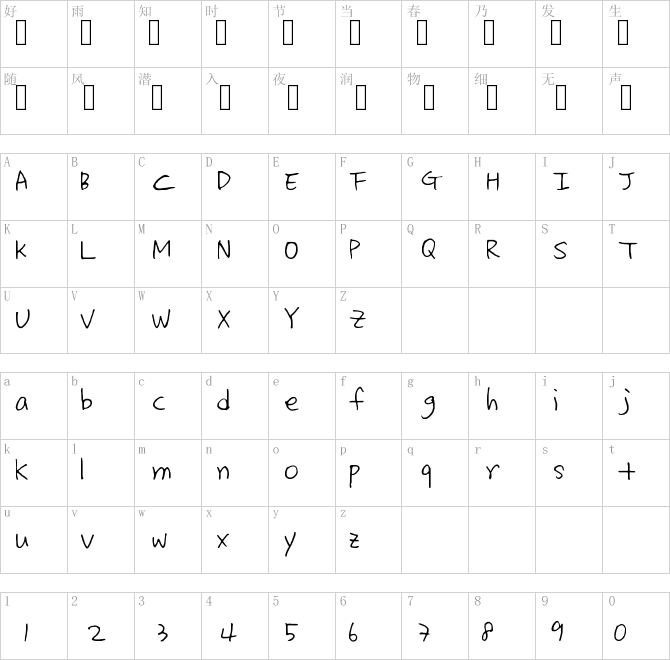
나눔손글씨 기쁨밝음韩国字体
나눔손글씨 기쁨밝음韩国字体,这款字体结构工整、笔画清晰,兼顾美观与易读性,适用于标题、正文、海报、包装、LOGO 等多种场景。字形优雅稳定,风格百搭耐看,适配日常排版与创意设计,让文字呈现更舒适、更具质感。나눔손글씨 기쁨밝음韩国字体一笔一画,皆是细节,以均衡的比例、流畅的线条打造舒适视觉体验,字形端正大气,风格简约现代。无论是商业设计、品牌宣传还是日常排版,都能轻松驾驭,让文字更有格调与力量。나눔손글씨 기쁨밝음韩国字体字体下载。
• 字体名称:나눔손글씨 기쁨밝음
• 字体标识:CLOVA OCR : Nanum GiBbeumBarkEum
• 字体全称:나눔손글씨 기쁨밝음